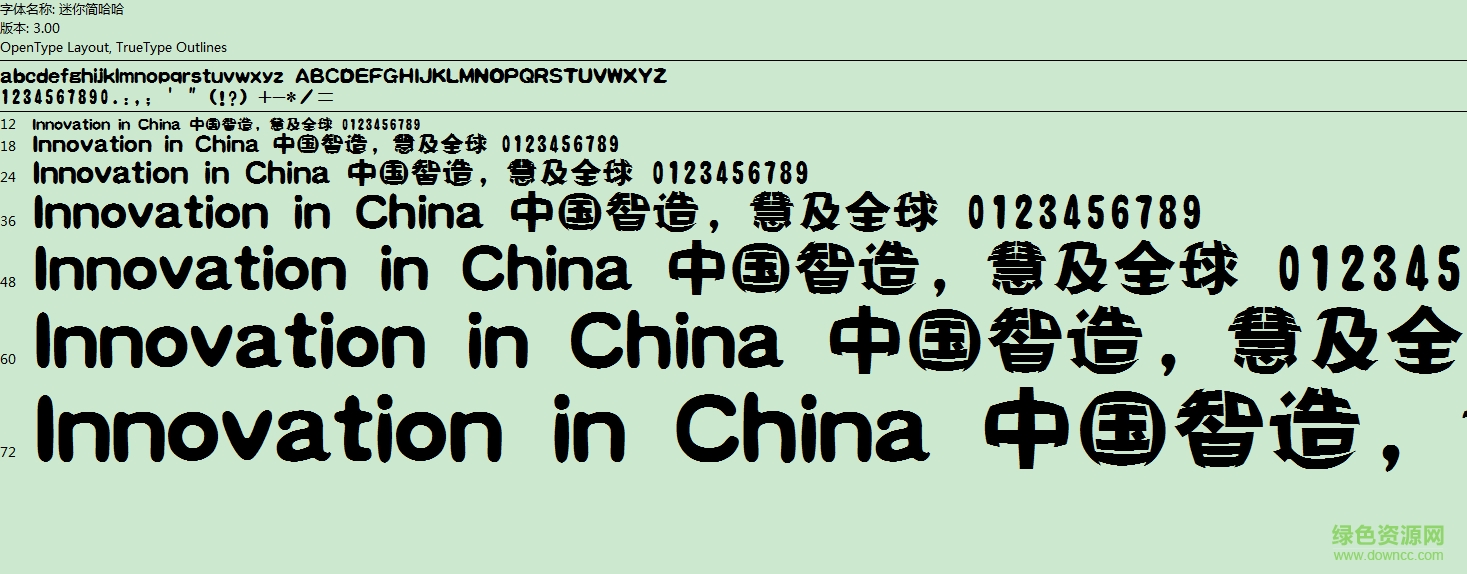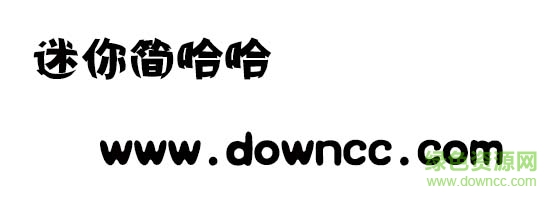
迷你簡(jiǎn)哈哈字體是一款以哈哈鏡為原型設(shè)計(jì)的迷你字體的一種,這款字體展現(xiàn)出來(lái)的效果類(lèi)似圓形,非常的有創(chuàng)意,有特色,喜歡這款字體的朋友歡迎來(lái)綠色資源網(wǎng)下載體驗(yàn)!
迷你簡(jiǎn)哈哈字體是一款應(yīng)用于廣告創(chuàng)意設(shè)計(jì)的簡(jiǎn)體中文漢字,該字體以哈哈鏡為原形而設(shè)計(jì),字形大方得體,整體出眾,并且字庫(kù)完整,可以適用于名片設(shè)計(jì)、平面設(shè)計(jì)、廣告設(shè)計(jì)、報(bào)紙雜志、企業(yè)LOGO、商標(biāo)注冊(cè)、電視臺(tái)廣告等領(lǐng)域,有喜歡的網(wǎng)友可免費(fèi)下載收藏。